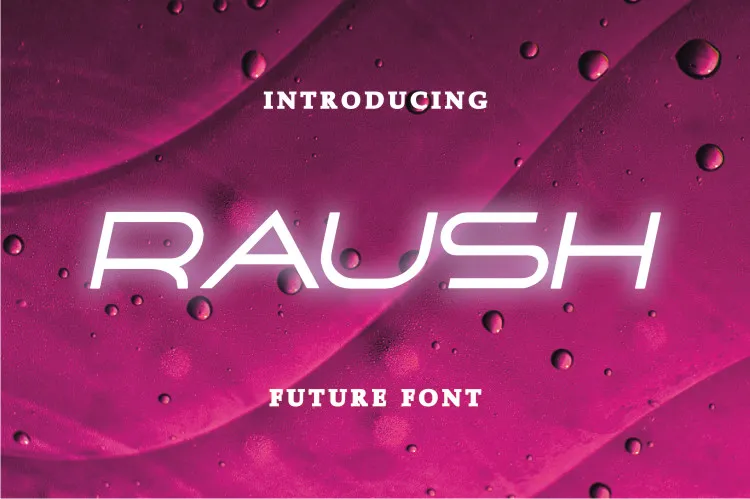
Raush Font
A Raush Font é uma elegante seleção para quem busca adicionar um toque tecnológico a seus projetos digitais. Esta fonte de display foi criada com um olhar moderno e apreciado por designers e criativos que buscam incorporar um visual único em suas criações web, identidades empresariais ou qualquer projeto que deseje destacar-se no campo digital atual. Suas linhas curvas dinâmicas e sua paleta de cores vibrantes ajudam a criar uma atmosfera hipersônica e futurista. Seja para personalizar o layout das suas páginas web, enriquecer as identidades visuais dos seus produtos ou criar um design editorial impactante, Raush Font é uma escolha inteligente que certamente impressionará seu público-alvo.